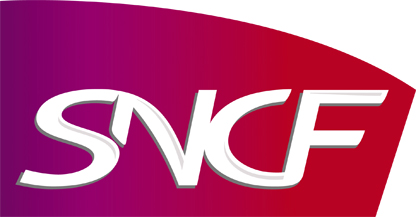
SNCF un logo dyslexique
Pourquoi dyslexique? Les orthophonistes vous en diront beaucoup plus que moi sur cette affection qui touche un grand nombre de personnes. S’agit-il seulement de confondre la gauche et la droite, ou de faire des fautes d’orthographe, ou de se précipiter dans des explications sans finir une phrase, les symptômes sont nombreux.
Le nouveau logo de la SNCF relève d’une stratégie de communication mûrement pensée, par des équipes de travail au sein de la compagnie de chemin de fer et au sein de l’agence Carré Noir. Nous savons tous comment ça fonctionne. De briefs en débiefings, semaine après semaine le projet évolue. Maquettes après maquettes, de validations en validations, personne ne prend, ou ne prend plus beaucoup de risque, et cela pourraît faire l’objet d’une note future concernant la dilution des responsabilités graphiques dans notre système économique. Nous sommes en tous cas loin d’une époque pas si lointaine, où les chefs d’entreprise, grands timmoniers de leur capitaux décidaient des orientations stratégiques de comm. propres à faire progresser leur entreprise.
C’est ainsi, et en préambule que je prendrai cette précaution de ne condamner personne pour avoir laissé passer ce logo contre toute logique de stratégie de communication.
Voici le débriefing de l’agence Carré Noir:
La couleur: un dégradé qui va du carmin au vermillon, fruit de «beaucoup de travail», a permis de créer la rupture, et d’exprimer l’innovation et la capacité créatrice de l’entreprise.
La forme: elle exprime pour certains un matériel roulant, pour d’autres un objet aérodynamique ou encore un livre ouvert, ou tout simplement une forme abstraite.
Un graphisme: «très dans la culture de la SNCF, ces quatre lettres dessinées en lien expriment la fluidité et le confort dans la relation entre Public et Salariés. Ce monogramme venu confirmer le nom d’une grande entreprise a été créé en CAPITALES pour ne pas céder avec des bas de casses (minuscules) à une expression trop originale ou rigolote. Elles s’enchaînent avec un lien entre elles pour qu’on sente qu’SNCF est un tout, de façon qu’à l’intérieur de ce bloc marque, on ait ce qu’on appelle un logotype.»
L’analyse:
L’histoire des logos tout d’abord:
Celle-ci témoigne de l’histoire socio-industrielle de notre pays. Vous trouverez un excellent résumé de la saga des logos de la SNCF ici.
Vous y voyez la représentation graphique du sigle SNCF et non du monogramme, vocable à l’usage expresse des personnes physiques et non morales (définition du sigle ici) qui correspond bien à la transformation industrielle de notre pays. De sigle en forme d’attribut de métiers on est passé à une écriture de plus en plus dépouillée de la typographie utilisée. Signe des temps sans doute, et puisqu’on parle de convivialité et de confort relationnel entre acteurs usagers et acteurs salariés, les dessins du TGV.
On est bien passé en 1947 par une représentation graphique proche de l’héraldique, et Michel Disle co-fondateur de Carré Noir nous explique le rôle que jouent ces signifiants dans la construction des identités visuelles modernes. Puis Roger Tallon intervient dans les années 80 sur le logo et la charte graphique de la SNCF alors qu’il venait de travailler sur le TGV.
Mais voici venir le nouveau logo du TGV :
En cherchant un peu, nous trouvons des similitudes avec une expression graphique chère au public nostalgique d’un temps idéal, l’art nouveau…
et encore…
C’est à ce moment de l’histoire qu’intervient la création du nouveau logo SNCF.
Celui-ci comme on le voit s’inscrit parfaitement dans la filiation des tracés ci-dessus. Mais il ne s’agit pas tant de dire j’aime ou j’aime pas, que de se poser la question si les quatres lettres du sigle-monogramme de la SCNF n’auraient pas été dessinées dans un style plus proche du métro parisien, donc aujourd’hui de la RATP que celui d’une entreprise dont la principale activité, le transport interrégional et international (thalys), riment avec puissance et vitesse. Nous ne voyons ni puissance dans ces quatres lettres, ni vitesse.
Le style fonctionnerait beaucoup mieux avec l’image d’un métro parisien de papa.
S’il s’agissait de réfléchir au logo de la RATP, nous en serions pour nos frais. Un cercle londonien vert pour ne pas froisser la Sa Majesté, et pour affirmer les valeurs modernes et consensuelles de l’écologie et du développement durable, et un tracé de la Seine en forme de visage plutôt féminin… une typo en Peignot italisé, c’est tout.
Tout ceci pour dire que nous sommes ici à contrario d’un logo de la Société Nationale des Chemins de Fer Français.
Et le Bloc-marque, en forme de matériel de roulement… là encore décalage entre le discours et le résultat. De forme aérodynamique nous n’en voyons pas, tout au plus un profil de TGV taillé à la serpe au lieu d’être tracé comme un geste calligraphique et élégant. En son temps Roger Excoffon en charge de la communication d’Air France avait innové en conférant à la compagnie, d’un geste aérodynamique et brossé à la Mathieu, une forme dont l’élégance et le pouvoir évocateur remplissaient parfaitement leur mission. Communiquer sur la modernité et l’alchimie d’une entreprise.